もともとデザイナー仲間で行う新年会用の遊びのために作られたという「フォントかるた」。それがSNSで話題となり、2017年2月に製品化、発売されました。48枚の取り札に書かれた文言はどれも「愛のあるユニークで豊かな書体。」。しかし、使われているフォントが全て異なります。フォント名を詠み上げて、そのフォントが使われている札を取る。そんなマニアックなかるたです。
どこかで目にしたあのフレーズ!
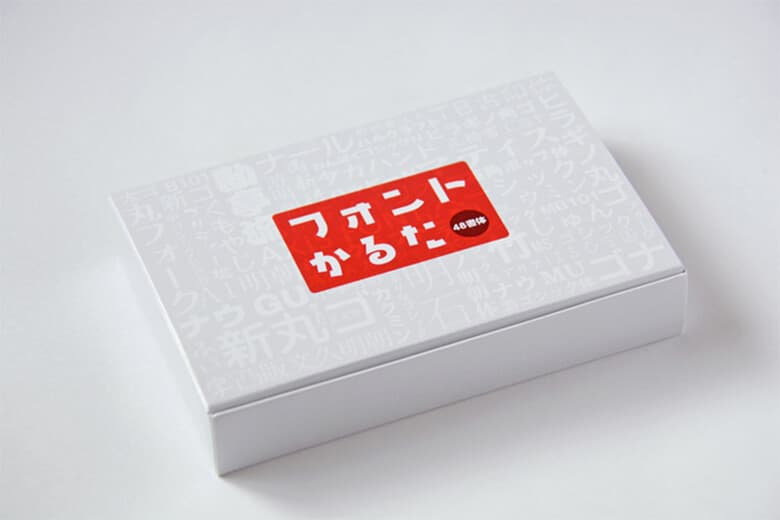
企画・デザインは、広告やエディトリアルを手がけるグラフィックデザイナーのせきね めぐみさん、解説は、グラフィックアプリケーションやデザイン関連書籍の執筆、グラフィックデザインのトレーニングを行っている伊達 千代さんが手がけた「フォントかるた」。
印刷されているのは「愛のあるユニークで豊かな書体。」。これは写植書体見本帳(写研)使われていたフレーズで、チーム全員一致で「これにしよう!」と採用されたんだそう。デザインに携わったことがある人なら1度は必ず目にしたことがあるこのフレーズに、思わず「そう来たか!」と声に出してしまった人もいるのでは…?
遊びながら学ぶ「まなび」のツール
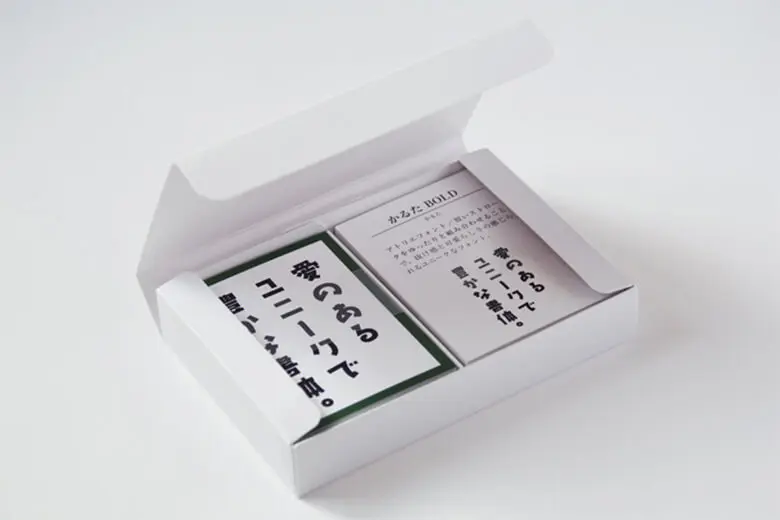
「フォントかるた制作チーム」のみなさんは、フォントかるたを単なる難しいゲームと考えているわけではないのだといいます。
「今までフォントに関心がなかった方でも、楽しみながら書体の違いが学べる絶好の「まなび」ツールだと考えています。フォントかるたをプレイすることで、街で見かけた書体を判別できるようになった小学生がいます。また、すでに高校・大学の授業の中で書体を学ぶ教材として使われていたり、印刷会社の研修に使いたいという要望もありました。一般の方々が、書体の面白さに気づき、書体の違いを知って、目的にあったフォントを選べるようになるために、フォントかるたがきっかけとなれることを、私たちはひとつの目標にしています」といいます。
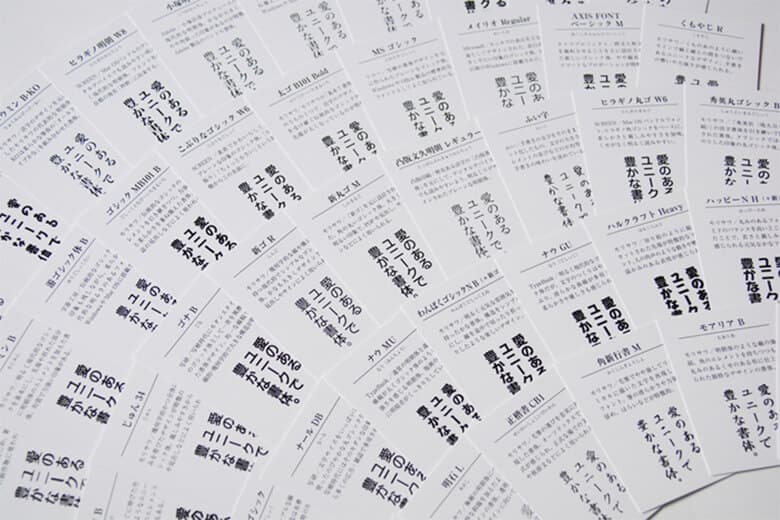
「まなび」ツールと考えているのも納得。読み札の裏には、フォント名・制作企業名・解説・そのフォントの文字が記されていて、フォントのことをよく知らない人でも興味を持ちやすくなっています。受験シーズンに持ち歩く「単語帳」のように、穴を開けて持ち歩きたくなってしまうような内容です。
「かるた」以外の遊び方も…?!
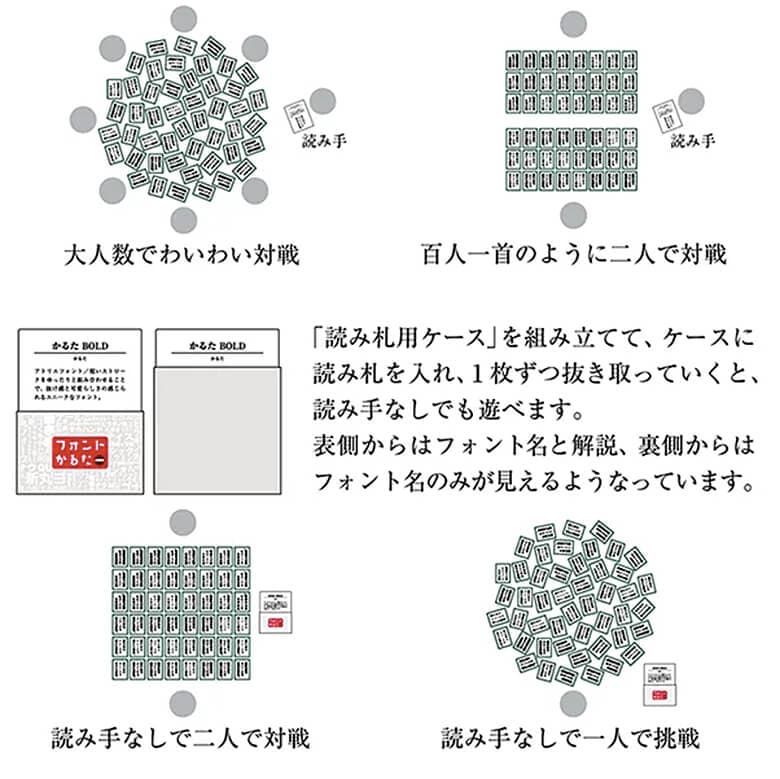
また、数種類の遊び方ができるのもポイント。大人数でワイワイとかるたを楽しむ以外に、百人一首のように札を整列させて対戦したり、付属の「読み札用ケース」を組み立てて、読み札を1枚ずつ抜き取りながら対戦、または1人で挑戦するという、読み手がなくても楽しめるような遊び方のアイデアが満載。
もともとは、新年会の余興として生まれたアイテムだけに、学びのツールとしてはもちろんのこと、遊びの延長で気軽にフォントと触れ合ってほしいという思いが遊び方の多さにも反映されています。ストイックに勉強したい方、かるたとして楽しみたい方、様々なニーズに答えた「フォントかるた」。まずは第一歩として気軽にホームパーティや旅行に持って行ってみてはいかがでしょう?